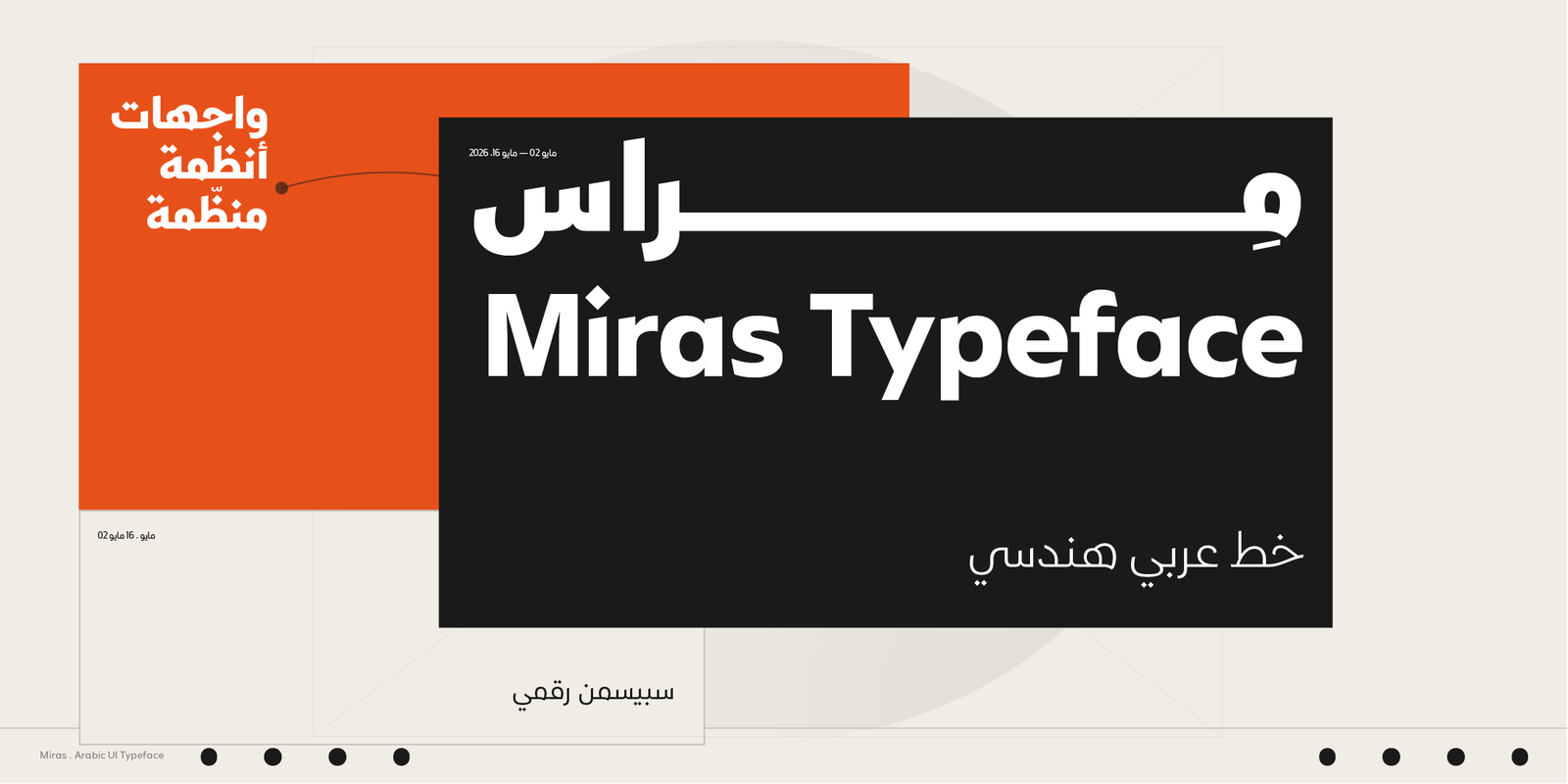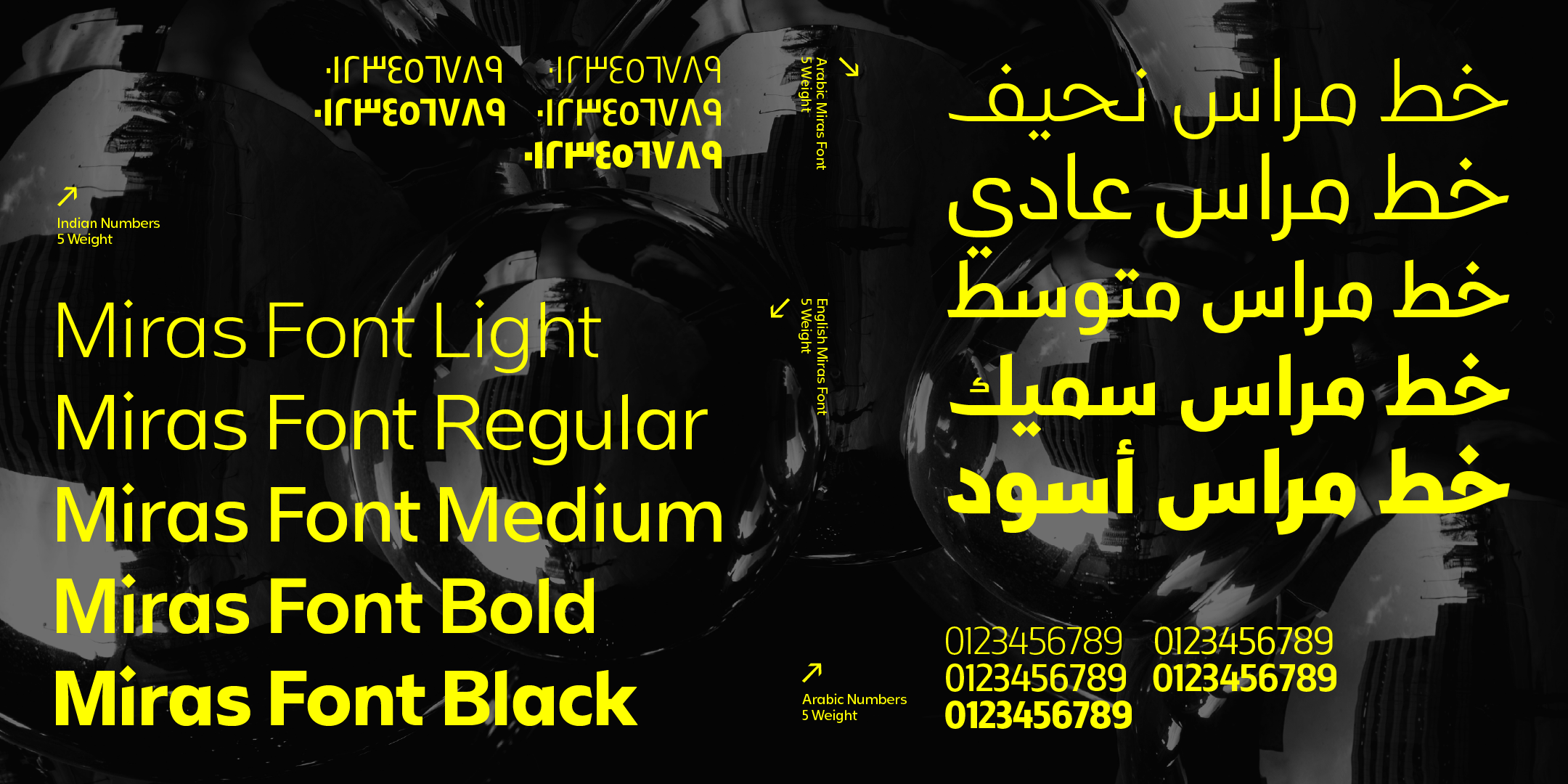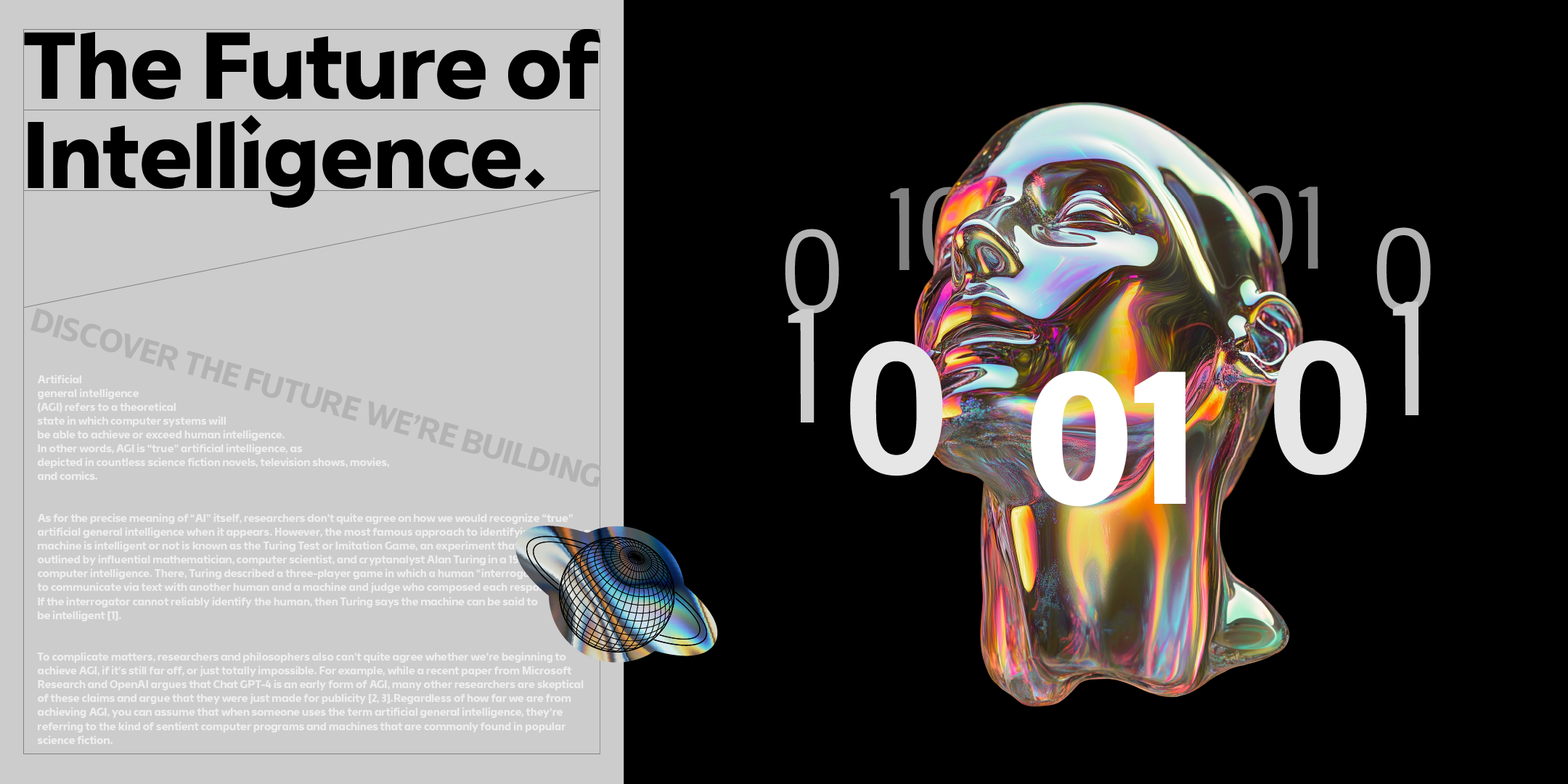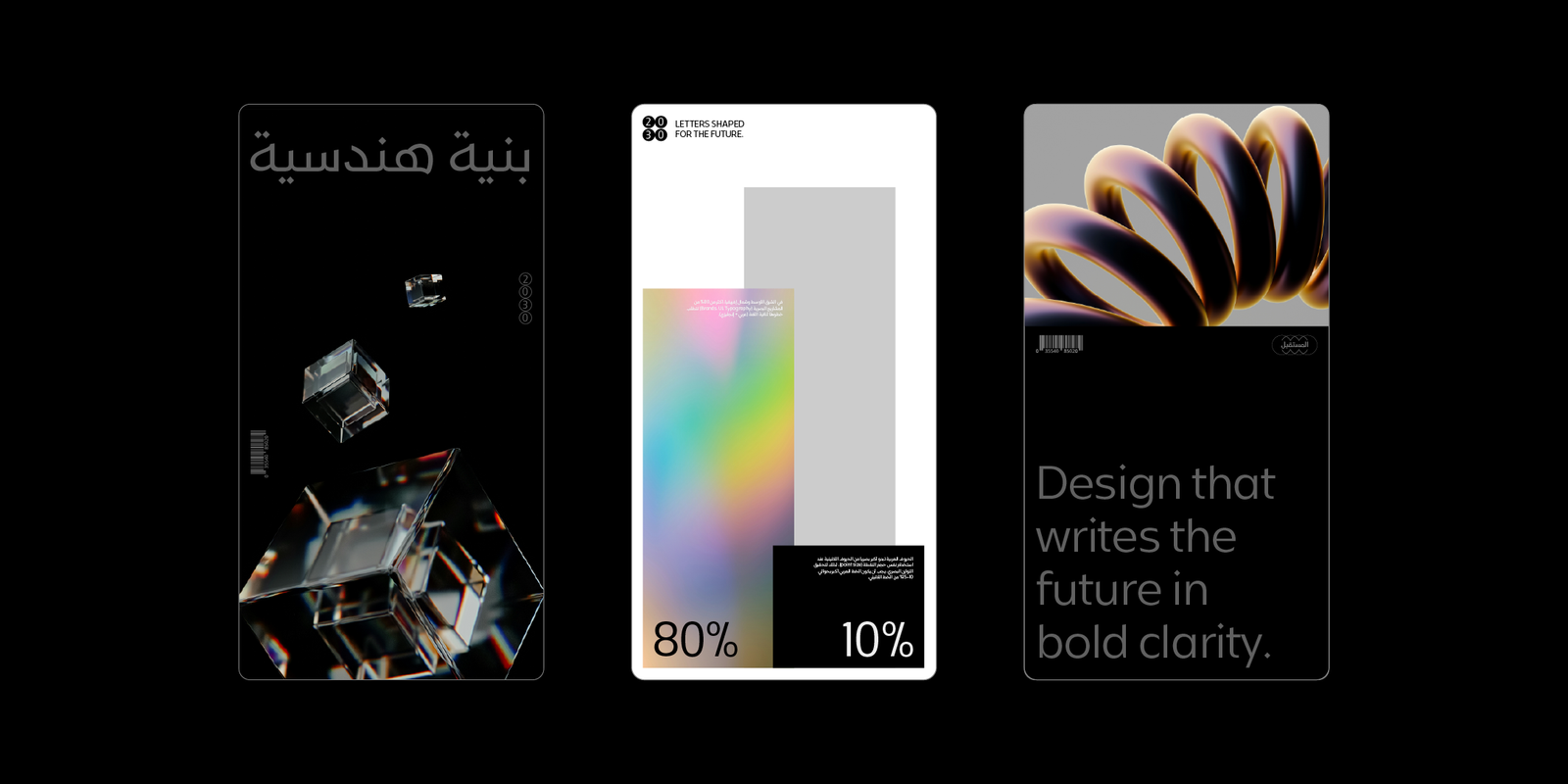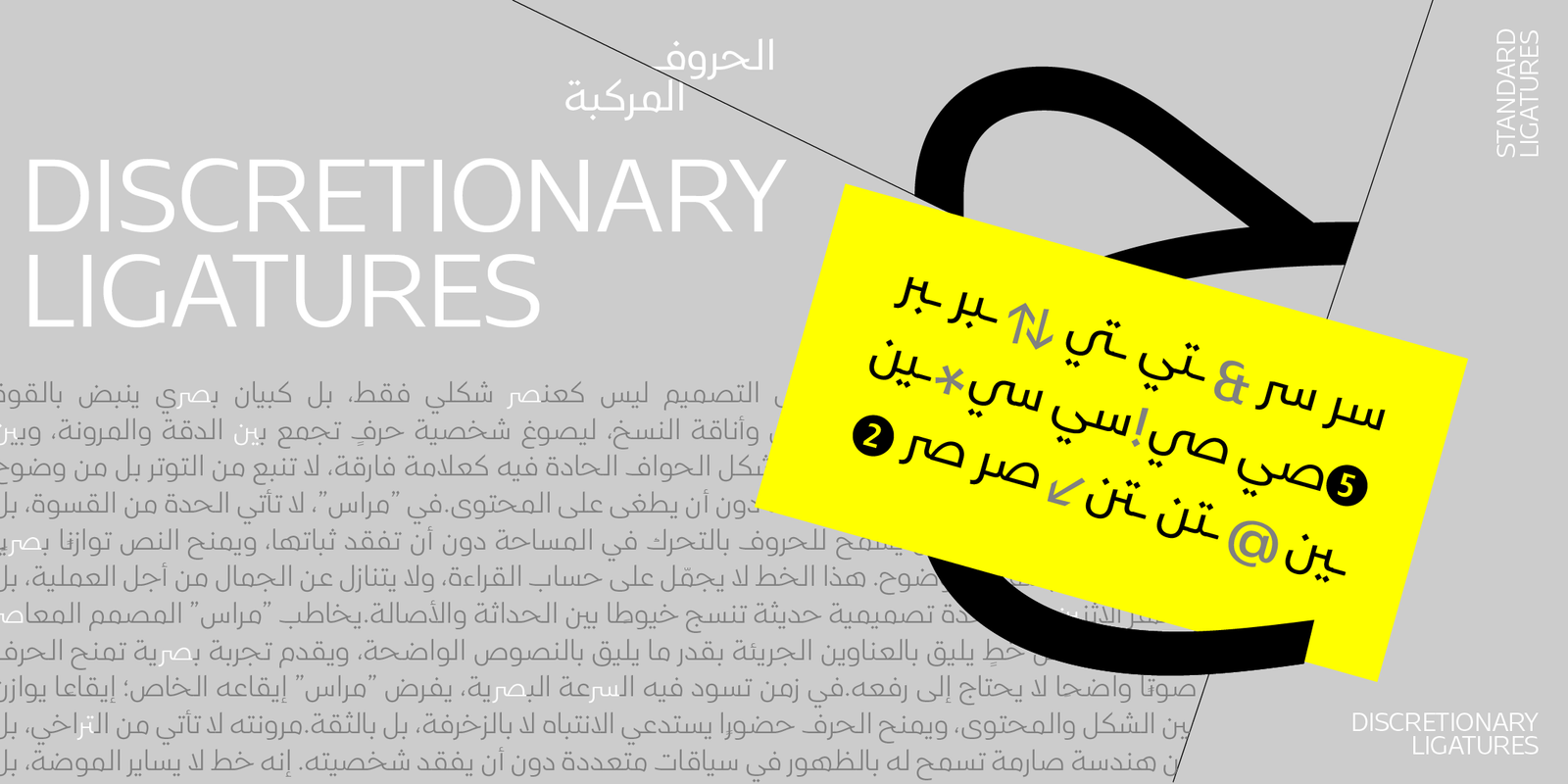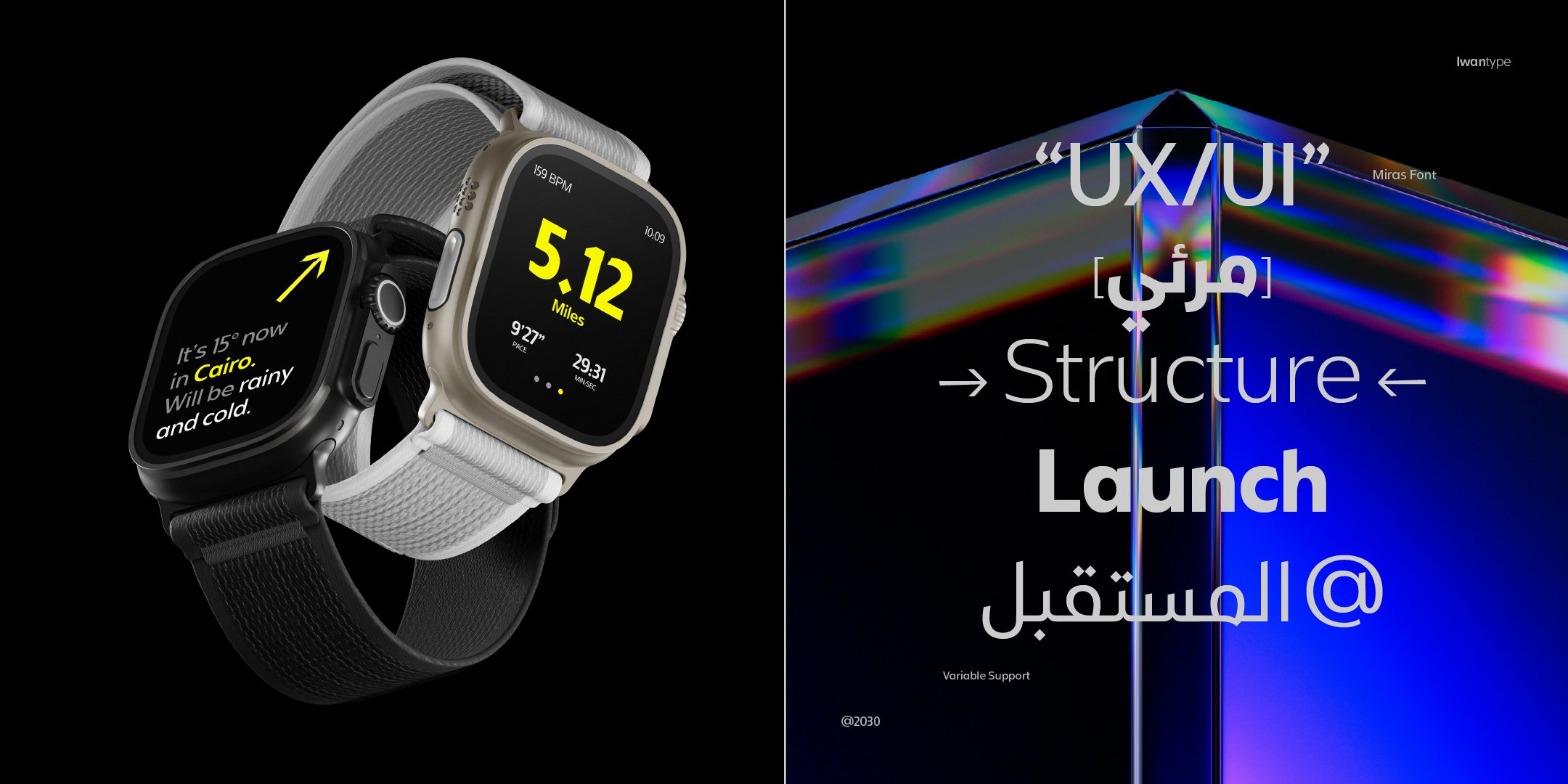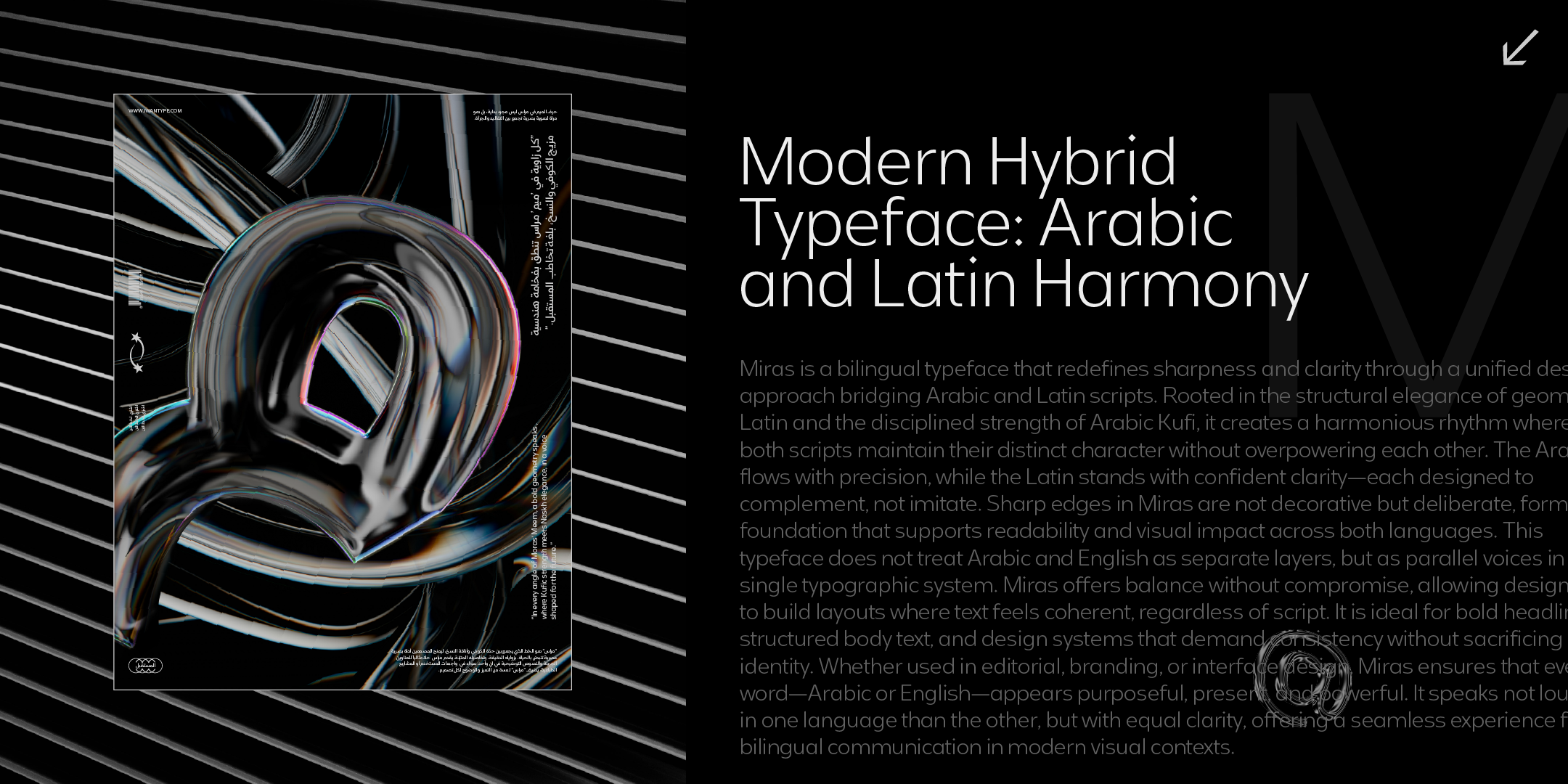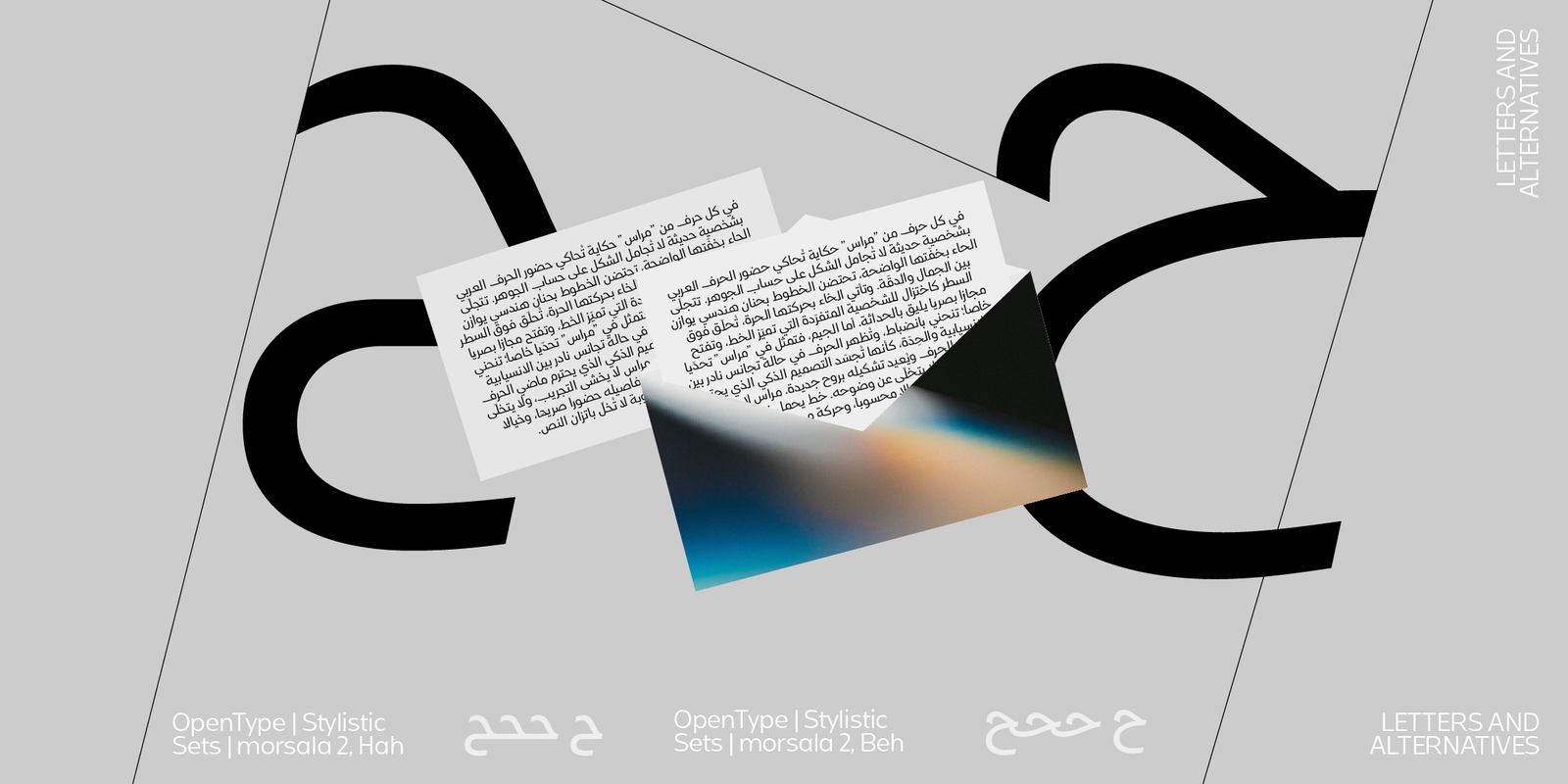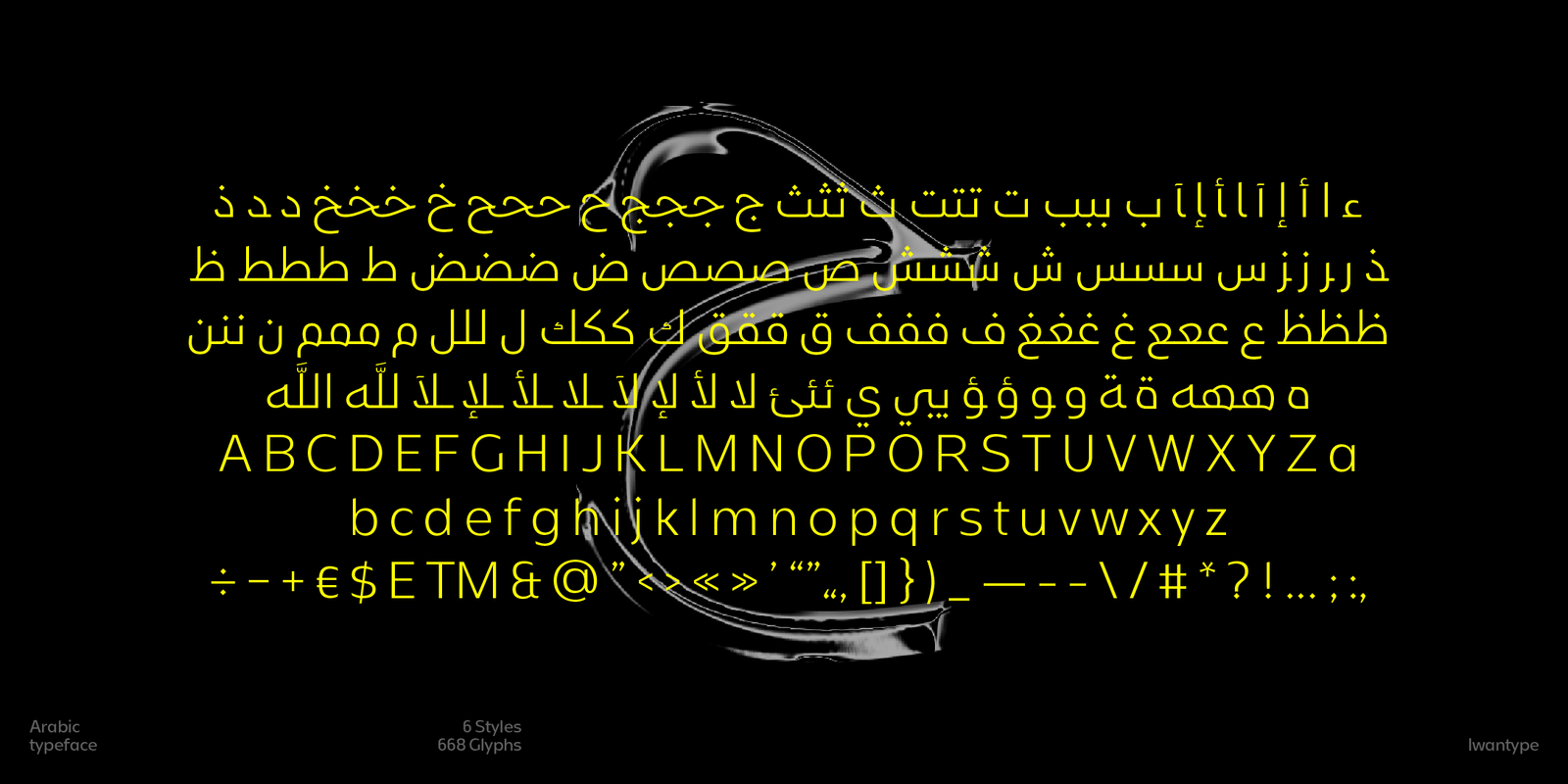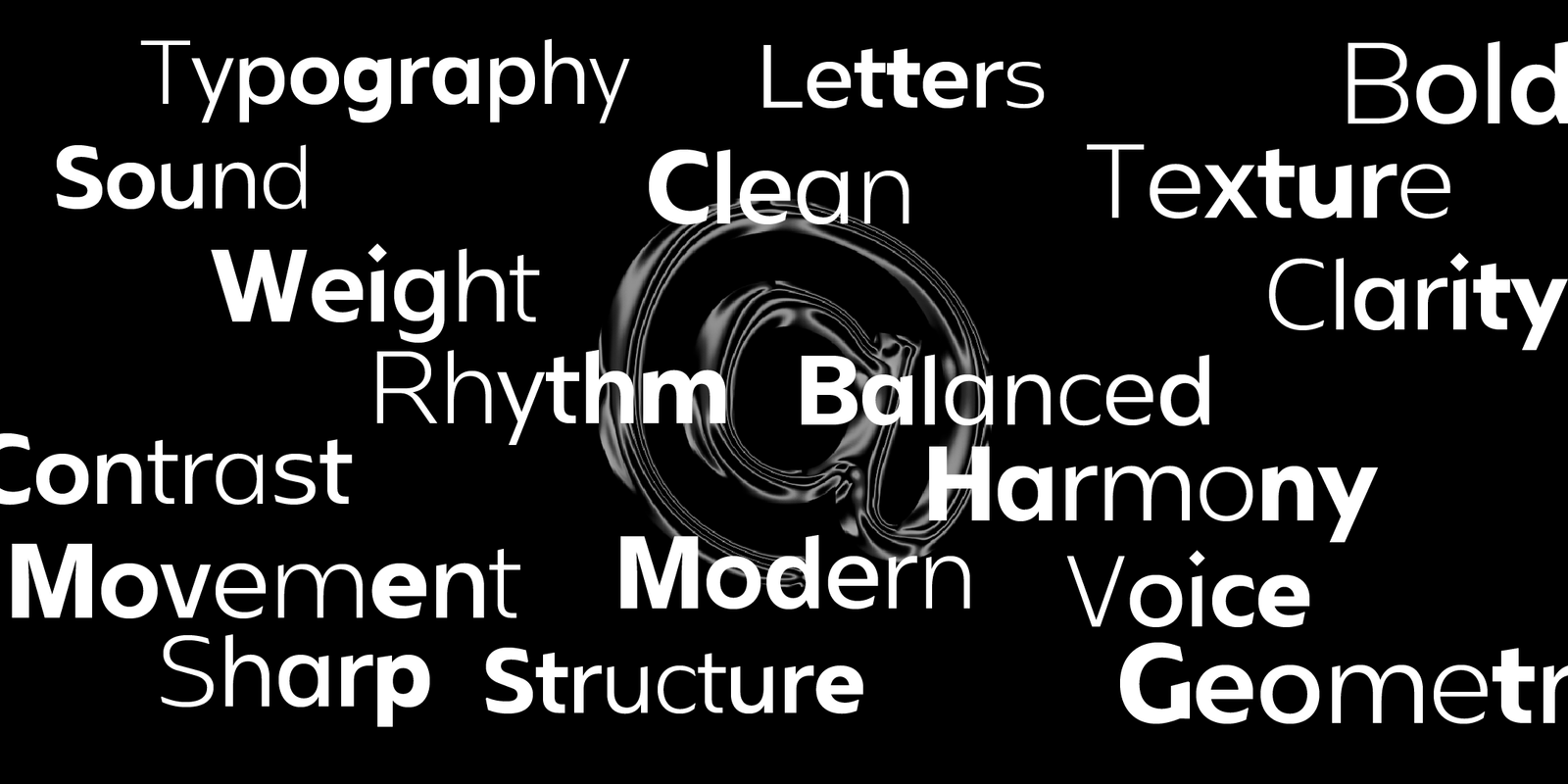
مِراس – خط عربي هندسي – Miras typeface
خط “مِراس” – حروف تكتب بلغة المستقبل
مِراس هو خط عربي هندسي معاصر، مصمم ليلائم متطلبات التصميم الرقمي الحديث، من تطبيقات الأجهزة الذكية إلى واجهات المستخدم والأنظمة التقنية.
تم تطوير الخط بدقة هندسية وتوازن بصري واضح، مع دعم لغوي شامل للعربية واللاتينية، ما يجعله مثاليًا للتصميمات التقنية والعلامات التجارية المستقبلية.
اللغات: العربية والانجليزية
الاوزان : خمسة اوزان
المميزات:
- أحرف بديلة لنزول اقصر مركبة
- أحرف بديلة لنزول اقصر
- أحرف مرسلة